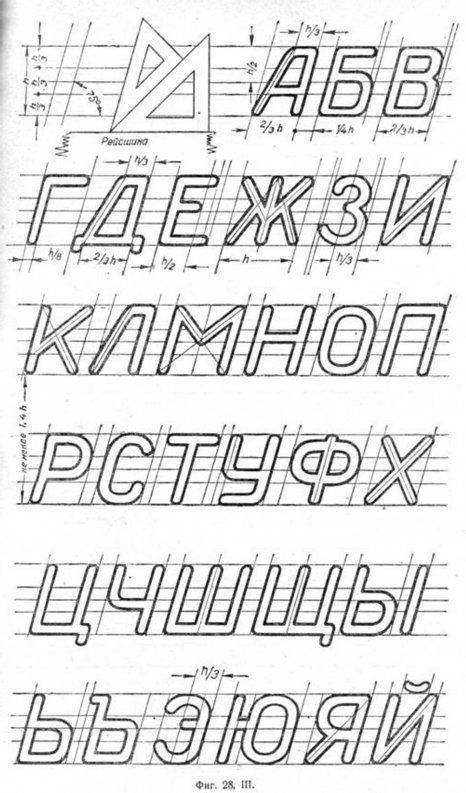
Буквы для черчения. Чертежный шрифт. Алфавит. Правила написания прописных букв и цыфр
Шрифт (от нем. Schrift) — это рисунок, начертание букв ка кого-либо алфавита, цифр и знаков.
Шрифты чертежные (ГОСТ 2.304-81) предназначены для выполнения надписей, начертания условных знаков и размерных чисел на чертежах. Для выполнения надписей в черчении используют ГОСТ. ГОСТ устанавливает номера чертежных шрифтов (1,8; 2,5; 3,5; 5; 7; 10; 14; 20; 28; 40) русского, латинского и других алфавитов.
Первый стандарт «Шрифты для надписей» был разработан и утвержден в 1919 г.
Номер шрифта соответствует высоте (h) прописной буквы. Например, шрифт № 5 имеет высоту прописной буквы, равную 5 мм.
Высота буквы измеряется перпендикулярно к основанию строки. Шрифт выполняется с наклоном в 75° (ГОСТом допускается выполнять надписи чертежным шрифтом без наклона).
Для удобства написания букв чертежного шрифта выстраивают вспомогательную сетку (рис.
35), которую выполняют следующим образом. Проводят нижнюю и верхнюю линии строки, расстояние между которыми равно высоте прописной буквы. Откладывают на нижней линии строки ширину букв и расстояние между ними (табл. 3).
Используя углы 45° и 30° угольников, строят наклон букв в строке, равный 75°.
Рассмотрите начертание букв чертежного шрифта (рис. 35— 37). Они различаются наличием горизонтальных, вертикальных, наклонных линий и закруглений, шириной и высотой. На рисунках показана (стрелками) последовательность начертания каждой буквы.
Рис. 35. Начертание прописных букв, состоящих из горизонтальных и вертикальных элементов, и построение вспомогательной сетки
рис. 36. Начертание прописных букв, состоящих из горизонтальных, вертикальных и наклонных элементов
Рис. 37. Начертание прописных букв, состоящих из прямолинейных и криволинейных элементов
Рис.
38. Начертание строчных букв, отличающихся от начертания прописных букв
Как вы, наверное, уже заметили, начертания многих строчных и прописных букв не отличаются между собой, например К — к, О — о и др. Начертание некоторых строчных букв отличается от начертания прописных (рис. 38).
При выполнении надписей следует учитывать, что нижние элементы прописных букв Д, Ц, Щ и верхний элемент буквы Й выполняют за счет расстояния между строк.
3. Размеры букв чертежного шрифта
Несмотря на то что расстояние между буквами определено стандартом, оно должно изменяться в зависимости от того, какое начертание имеют рядом стоящие буквы. Например, в слове РАБОТА (рис. 39, а) расстоянием между буквой P и A, T и А необходимо пренебречь (т. е. расстояние должно быть равно нулю), поскольку их начертание зрительно создает достаточный межбуквенный просвет. По этой же причине стандартное расстояние между буквами Б и О, 0 и T следует сократить вполовину.
Рис. 39. Учет межбуквенного просвета при написании слов: а — правильно; б — неправильно
Рис. 40. Цифры и знаки
Начертание цифр и знаков показано на рисунке 40. (При выполнении чертежей выбирайте высоту шрифта не менее 3,5 мм.)
Шрифты — Техническое черчение
Чёткость и наглядность чертежа зависят от качества его оформления. Чертежи, правильно вычерченные, но имеющие плохо выполненные надписи, теряют вид. При выполнении надписей необходимо обращать внимание на то, чтобы размеры выбранных для надписей шрифтов гармонировали с размерами чертёжного листа. Чтобы научиться хорошо писать, необходима тренировка.
Каждый чертёж содержит различные надписи, состоящие из букв и цифр. При изучении шрифта следует ознакомиться вначале с конструкцией букв и цифр, затем переходить к надписям.
На машиностроительных чертежах надписи должны быть выполнены стандартным шрифтом по ГОСТ 3454-46. Этот шрифт прост по своему начертанию и быстро осваивается. Конструкция букв’ и цифр стандартного шрифта приведена на фиг. 28, I и II.
Изучение шрифтов рекомендуется начинать с крупных размеров шрифта, например с 14-го, и постепенно переходить к более мелким размерам, не стремясь при этом придерживаться алфавитного порядка, а принимая лишь во внимание возрастающую степень трудности начертания букв и цифр.
При изучении чертёжного шрифта необходимо построить тонкими линиями, карандашом HB или H графическую сетку с соблюдением основных соотношений по высоте выбранного шрифта, а затем нанести от руки на эту сетку буквы и цифры. Проверив правильность начертания шрифта, можно приступить к обводке его тушью. Обводка выполняется простыми, а также специальными трубчатыми или воронкообразными перьями (фиг. 26). В практике для нанесения шрифтовых надписей с успехом пользуются нормографами (фиг.
27), представляющими собой целлулоидные пластинки, в которых имеются отверстия, соответствующие очертаниям элементов букв. Накладывая нормограф на бумагу и передвигая его по рейсшине или линейке, можно, не делая предварительно графической сетки, писать тушью чертёжный шрифт рейсфедером или же трубчатыми перьями соответствующих размеров.